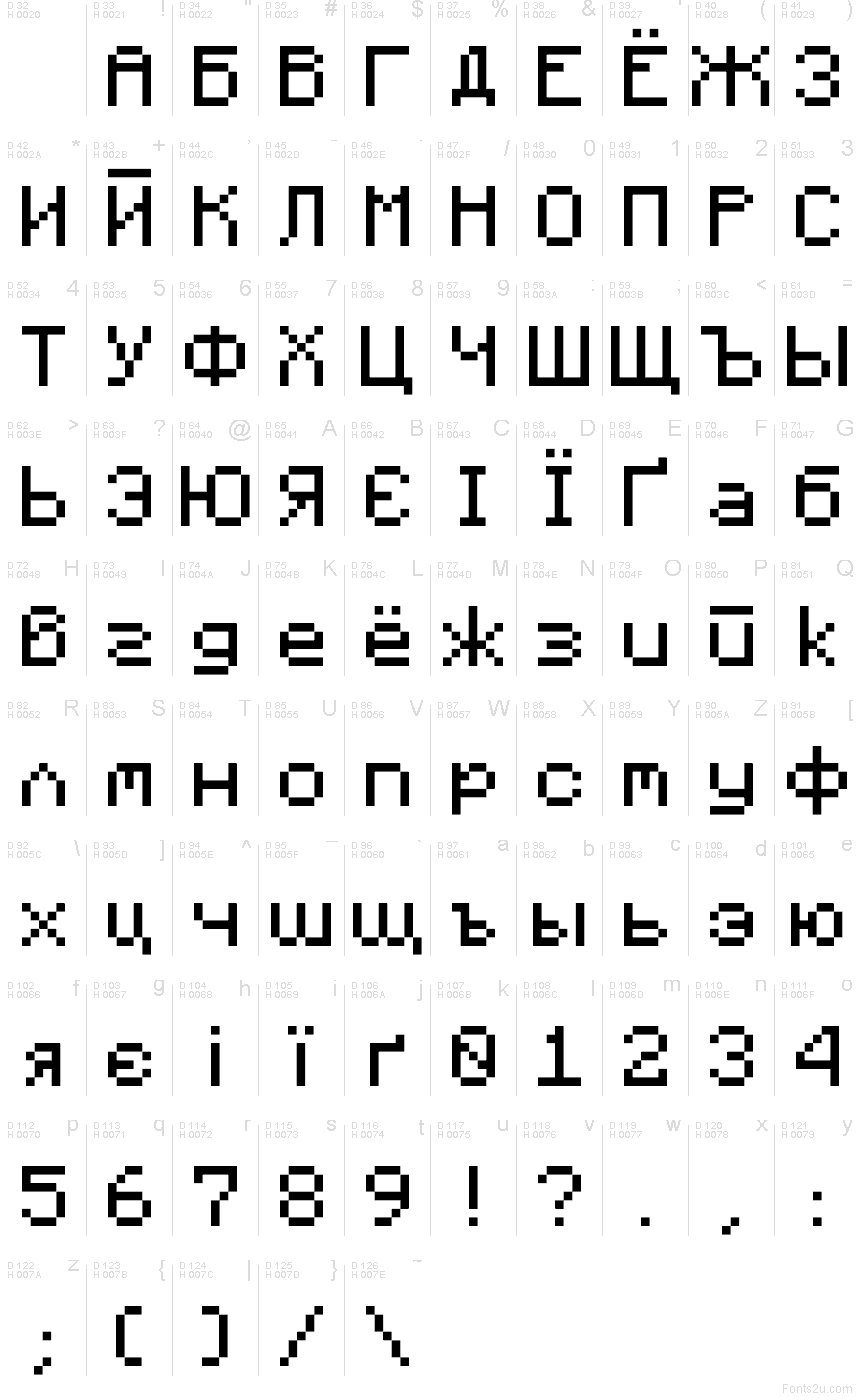
Pixelando Regular Písmo
Pixelando od GallGricela je bezplatný pixelový font s přímočarým rytmem starých obrazovek a lehkým nádechem ruských plakátů. Písmena jsou sestavena z čtvercových schůdků a ostrých hran, takže celý font působí stroze, mechanicky a tak trochu herně, rozhodně ne uhlazeně.
Díky tomu je přirozenou volbou pro branding retro her, zinů, elektronických letáků, titulků, plakátových nadpisů a krátkých popisků inspirovaných UI, kde bezplatný font dokáže vykouzlit low-res atmosféru bez zbytečných efektů. Nejlépe funguje v krátkých dávkách, protože masivní rastr a useknuté siluety dodávají krátkým slovům, titulkům a kompaktním logům záměrný, zakódovaný náboj.